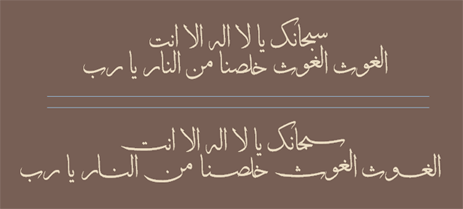
فونت ثلث
نسخه جدید فونت ثلث
الف‌های کشیده و بلند و دوایر نسبتاً کم عمق و باز از خصوصیات این خط است. در خط ثلث کلمات گاهی مجزا و گاه خیلی تو در تو و سوار بر یکدیگر نوشته می‌شوند که به این علت گاهی خوانایی آن کم می‌شود.
این خط از لحاظ ظاهری بی شباهت به خط محقق نیست با این تفاوت که در این خط برخلاف محقق دور حروف بیشتر و اندازه آن‌ها کوچکتر است. در ثلث، حروف و کلمات، درشت ولی جمع و جورتر از محقق بوده و حلقه‌ها و گره‌ها باز و در برخی موارد بسته می‌گردند.
این فونت براساس فونت ثلث نرم افزار میرعماد ساخته شده است و با فونت ثلث های سابق تفاوت دارد. از تفاوت های ویژه این فونت میتوان به قابلیت کشیدگی اکثر حروف (با استفاده از SHIFT+J) اشاره کرد. و در نرم افزارهای تایپ پیشفرض ویندوز (NOTEPAD ,WORDPAD) و مایکروسافت آفیس به خوبی عمل می‌کند ولی در نرم افزارهای گرافیکی فتوشاپ، کرل، ایندیزاین و… عمل  نمی کند. برای استفاده در فتوشاپ میتوانید متن تایپ شده را در نرم افزار ورد به فایل پی‌دی‌اف تبدیل کرده و آن را به محیط گرافیکی مورد نظر انتقال دهید.